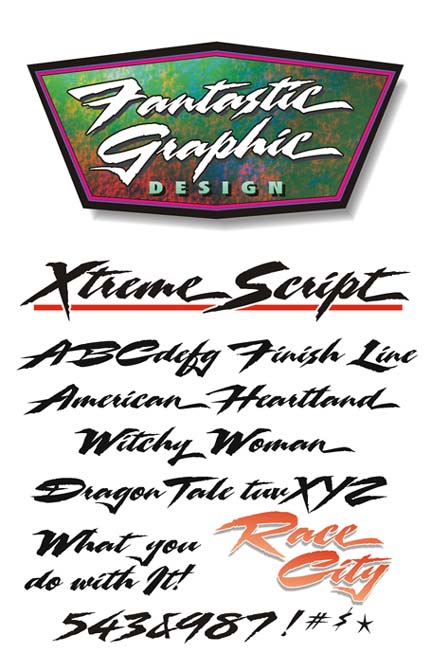
Logo oder Schriftart?
ich suche die schriftart mit der dieser schriftzug erstellt wurde. oder ist das eher ein gezeichnetes logo?
hinweise zu alternative schriftarten sind auch gerne gesehen.
Sieht nach Logo aus. Ähnlich wäre die "Xtreme Script"